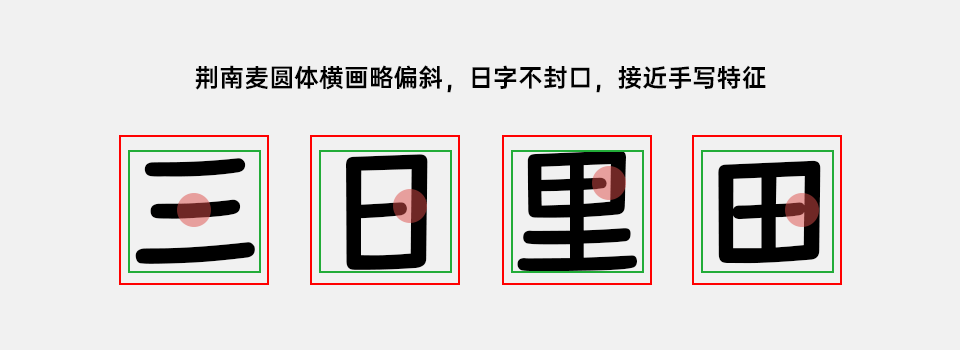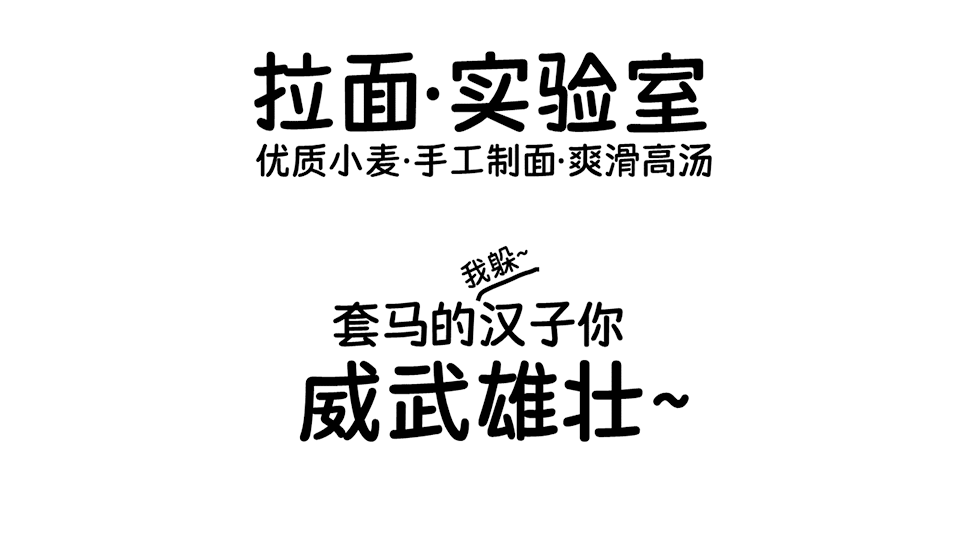
荆南麦圆体(Kingnam Maiyuan)是由荆南字坊推出的一款免费商用中文字体,设计灵感源自韩国综艺中的谚文字体。设计师发现韩文字体中有很多独特的手写圆润风格,而这在当时的中文字体中相对较少,因此尝试将这种风格移植到汉字设计中,也就形成了这款中文萌系手写圆体。
字体笔画均匀圆润,粗细基本一致,两端做饱满圆弧处理;横画略倾斜、“日” 字不封口,保留手写的自然感,但不连笔,辨识度远优于很多潦草手写体。字间距也比较适中,避免拥挤模糊,小字号屏幕显示依然清晰,大标题则更显软萌活力。尤为适合食品类、母婴类、儿童类的设计场景,无论是海报标题、广告设计,还是文创产品制作等。